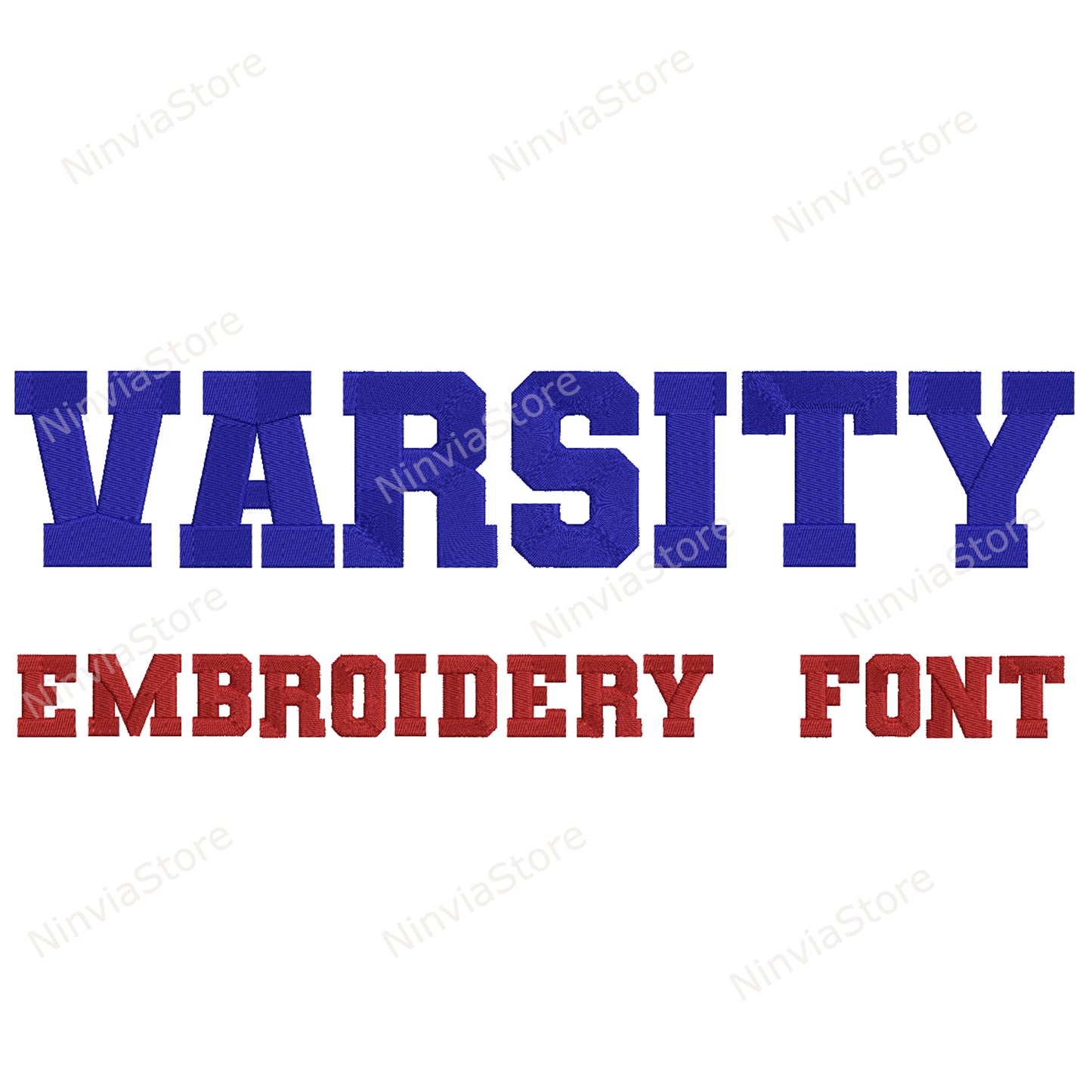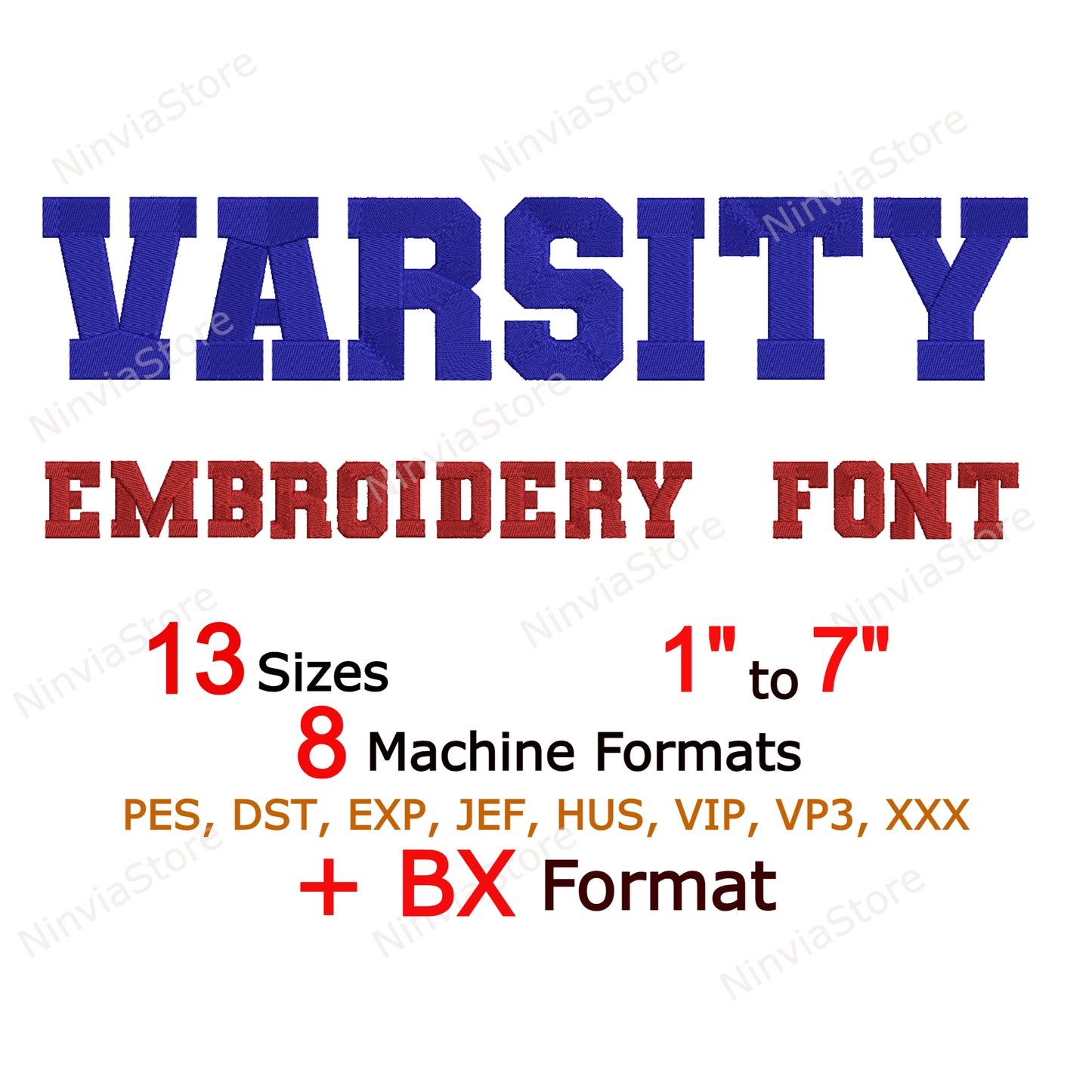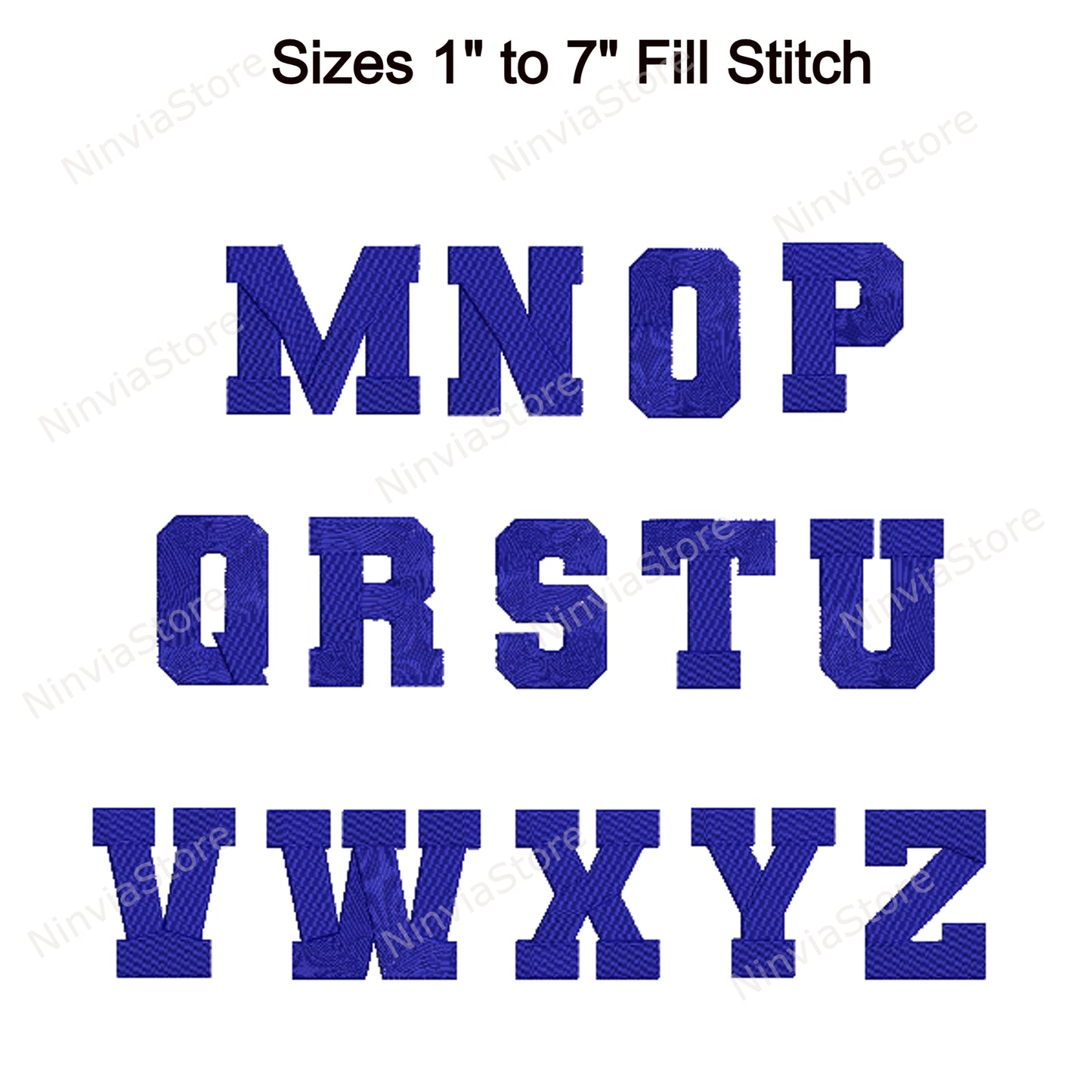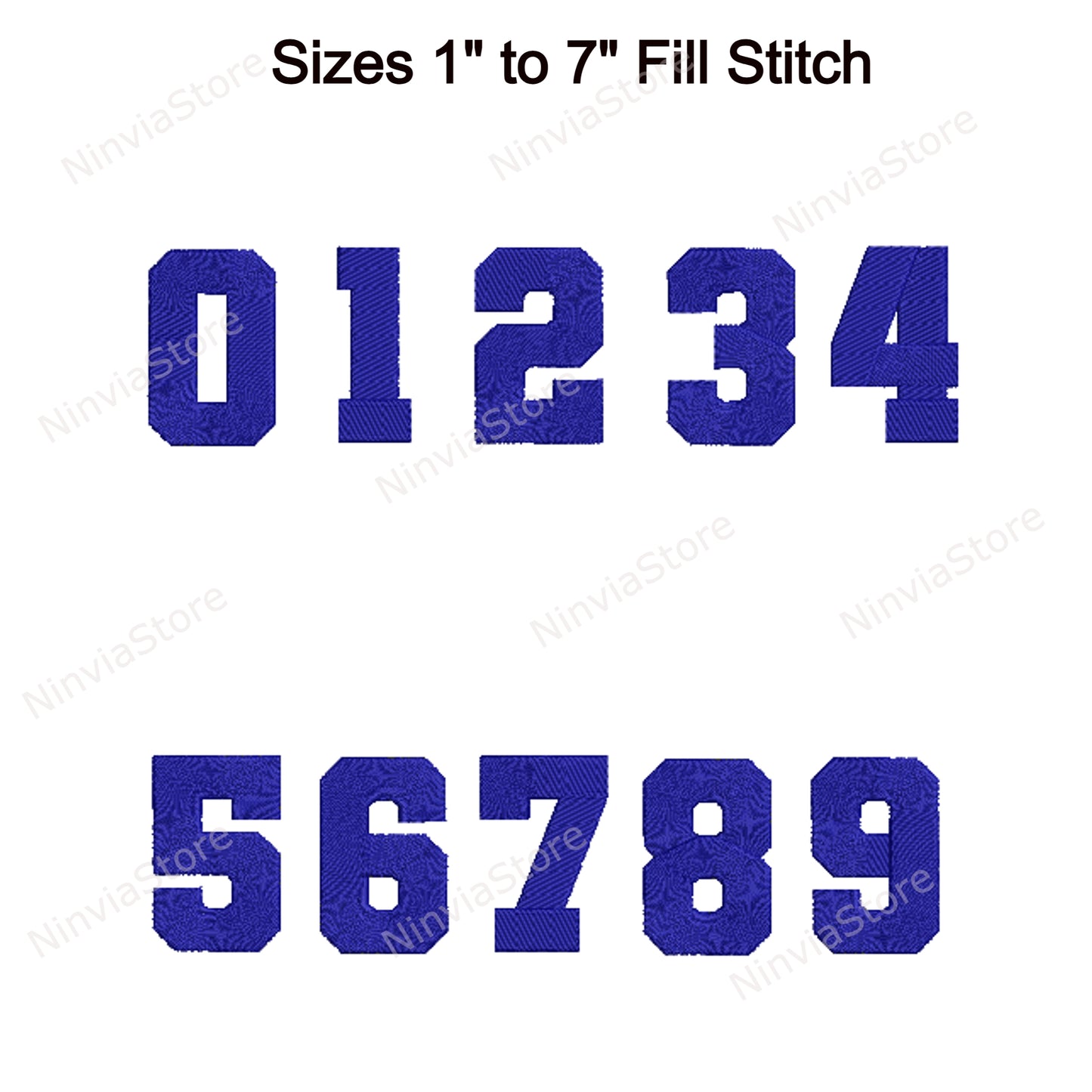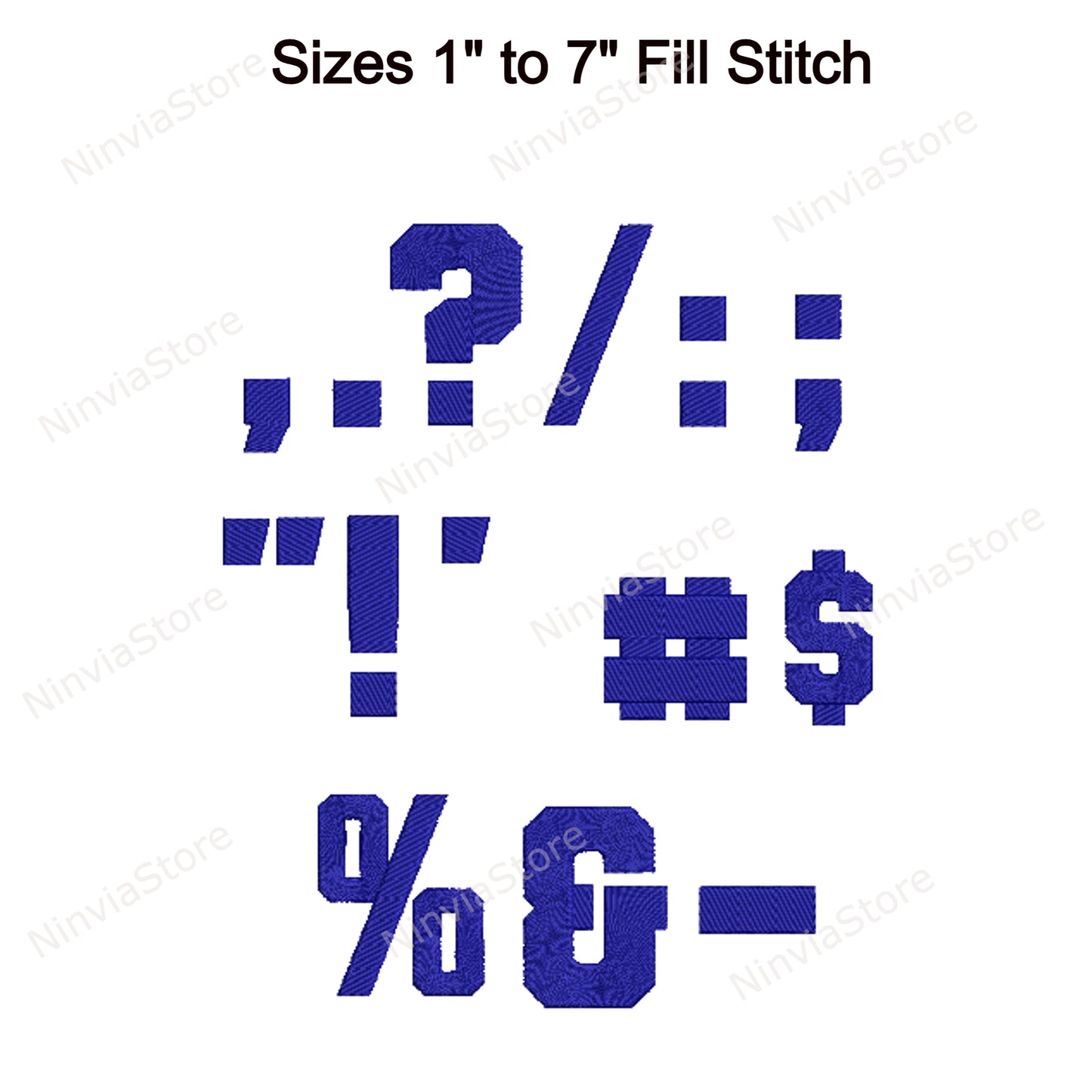
Police de broderie machine Varsity 2 couleurs, 15 tailles, 8 formats, police BX, police PE, motifs de broderie Monogram Alphabet
La police de broderie monogramme universitaire 2 couleurs est disponible en téléchargement instantané.